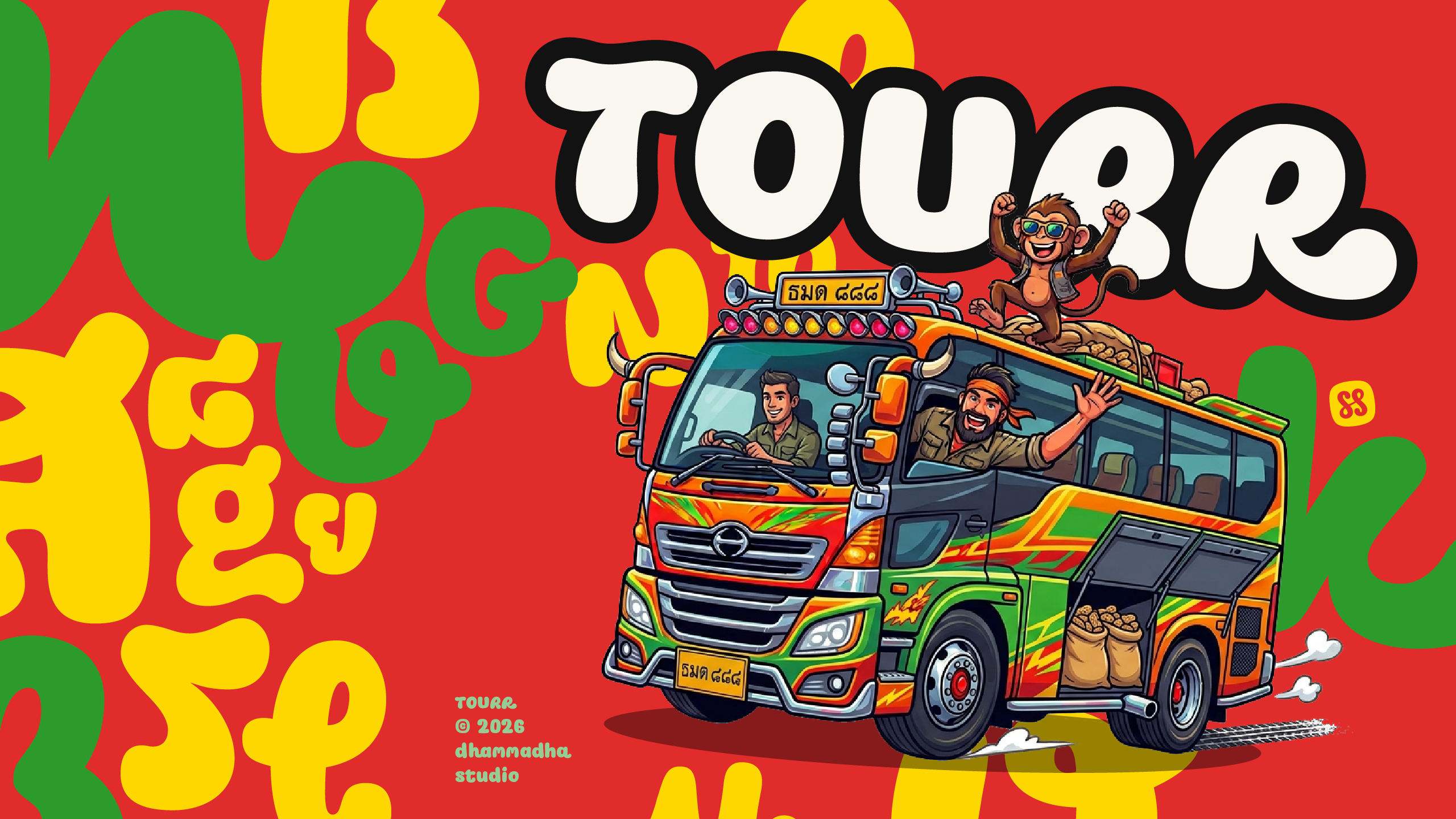
ถั่ว | TOURR
ปอมป๋วย
ต่อยอดจากสเก็ตช์แรกในชีวิตเมื่อสิบกว่าปีก่อน
แต่ทำแบบที่เคยคิดไม่ได้แล้ว
เลยออกมาแบบนี้
น่าร๊ากกกกก ทัวร์ ถั่ว ถัวๆ ทั่ว
ว้าย นุ่มนิ้ม  :25: